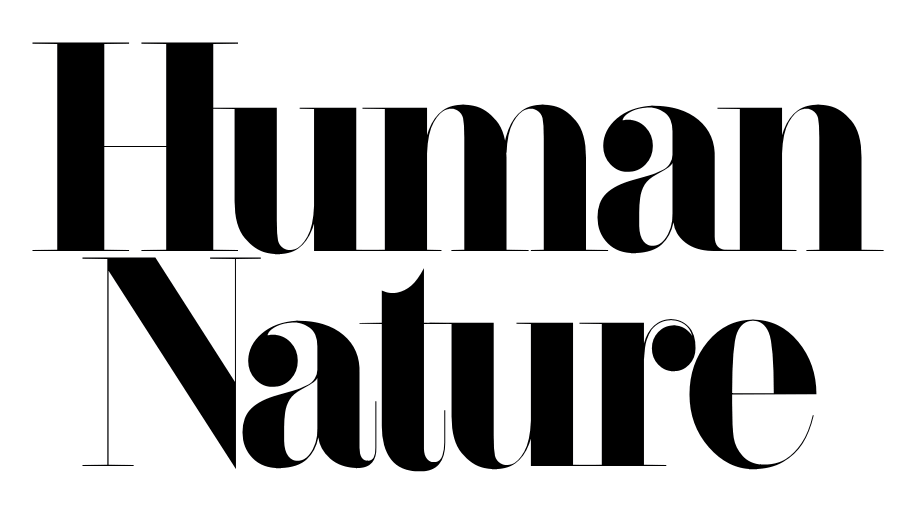
オリジナルフォント Didot DF |
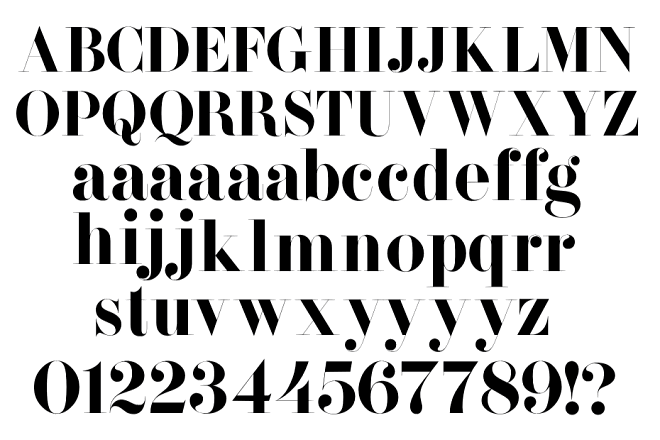
現在、作成中のオリジナルフォント「Didot DF」。
2008年12月頃につくりはじめ、そのまま放ったらかしの状態でした。
最近になって、再度見直し、一から作成。
オーパルな「O」など、全体的に
Didi をベースにしています。
ウエイトは、Didi
と
Firenze の中間くらい。
いままでの Didot だと、「R」や「a」の右側に文字がくると、カーニングなどの処理に困りましたが、
テールをフラットにしたオルタネートをつくることにより、問題を解決。
ケルン(「a」や「f」などにある玉部分)も2種類用意しました。 |
オリジナルフォント Caslon Swash DF |
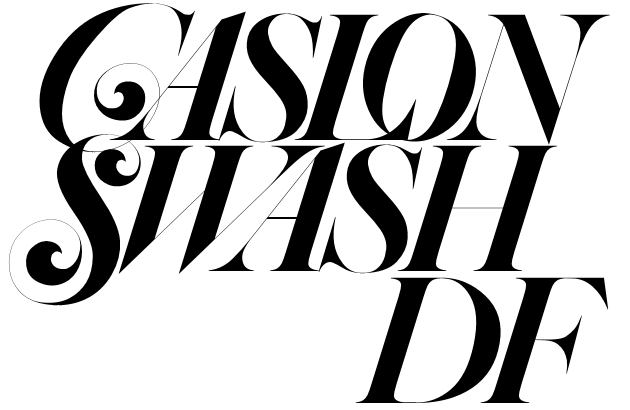
作成中のオリジナルフォント「Caslon Swash DF」。
この他にも10書体ほど同時進行で作成中です。